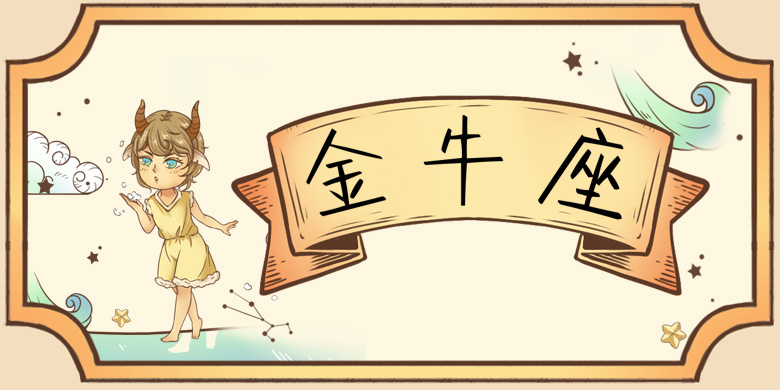
方正手迹-送你一根棒棒糖
字体说明
方正手迹-送你一根棒棒糖
字体英文名称:FZSJ-SONGNYGBBT.TTF
方正手迹-送你一根棒棒糖
品牌:方正手迹
设计师:
俞亦婷
发行时间:2019
字库编码:
大陆简体(GB2312-80)
分类:
创意书写
字体属性:
心动字
字体介绍
送你一根棒棒糖体,这款字体可爱的字形搭配简单易懂的图形文字,妙趣横生充满童趣。适用于少年儿童类的书刊、漫画综艺字幕、品牌广告和产品包装设计,以及社交网络的个性化用字。